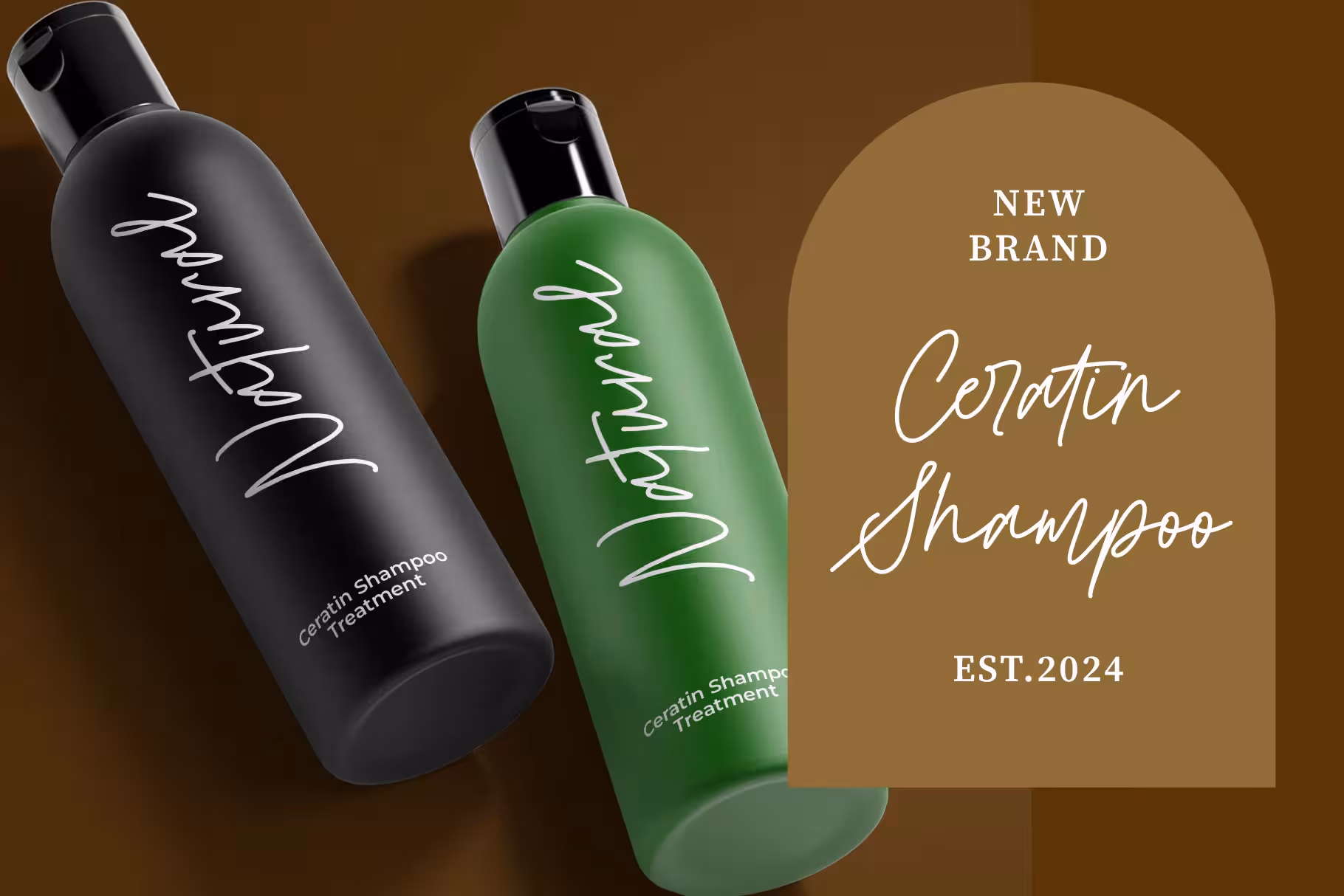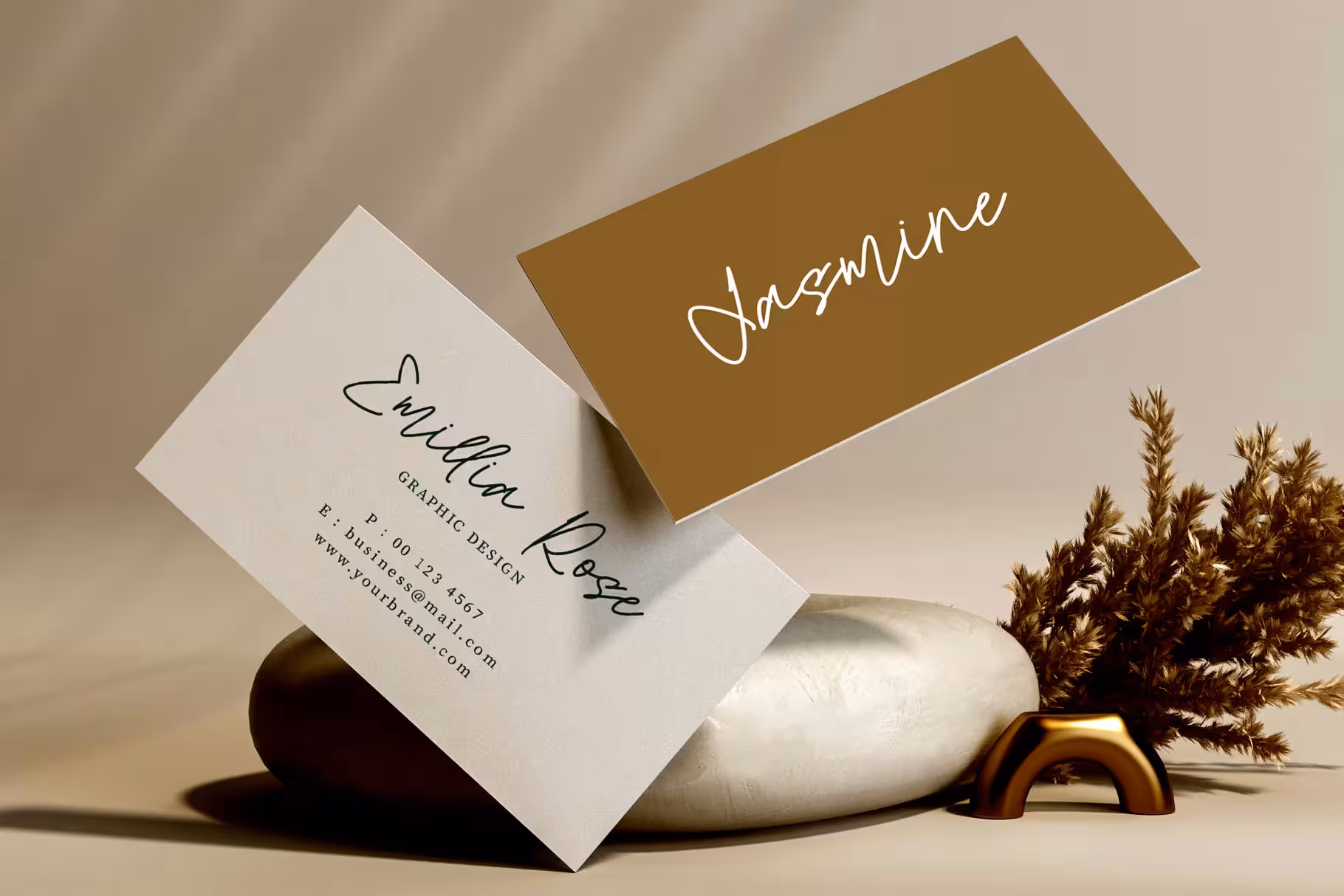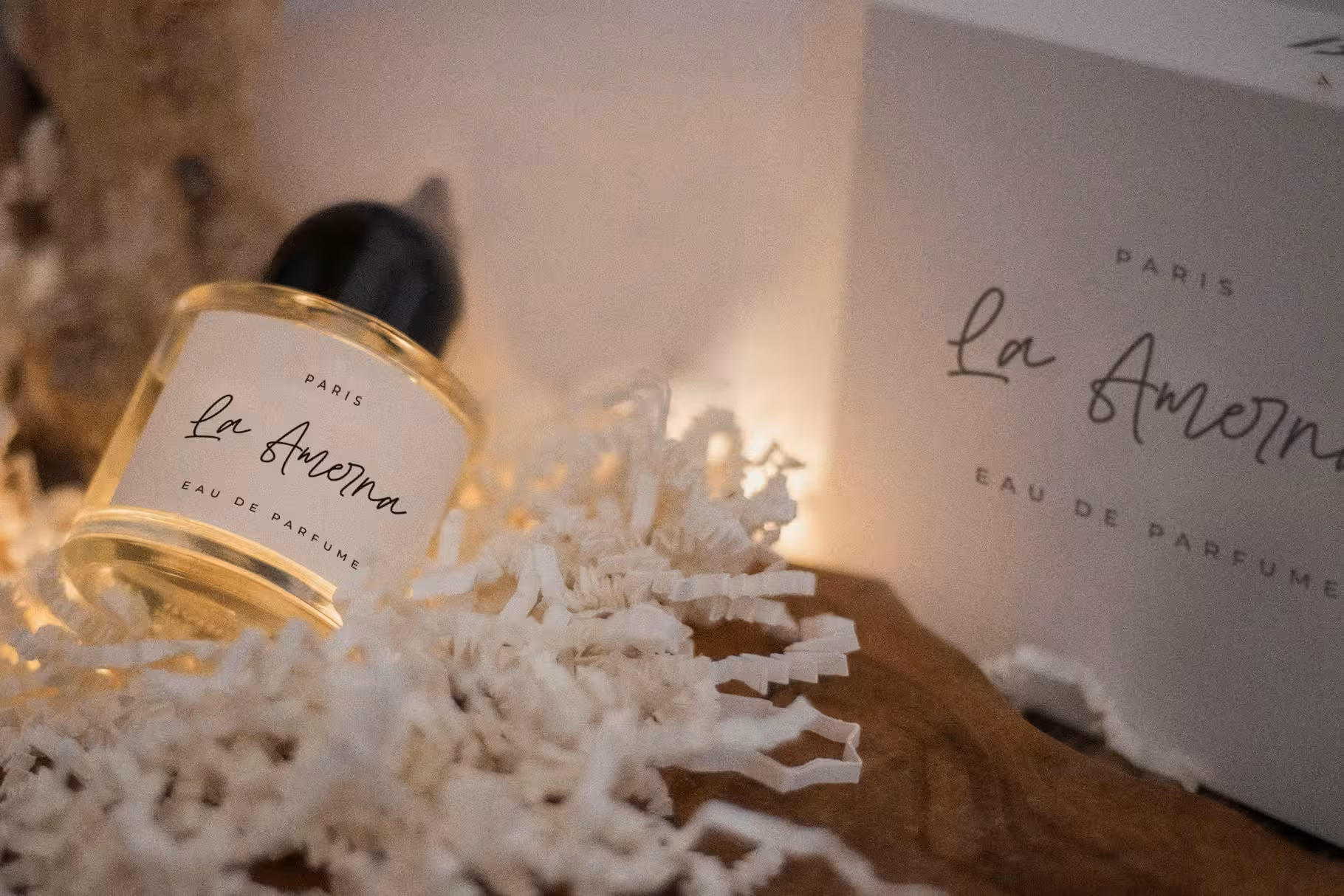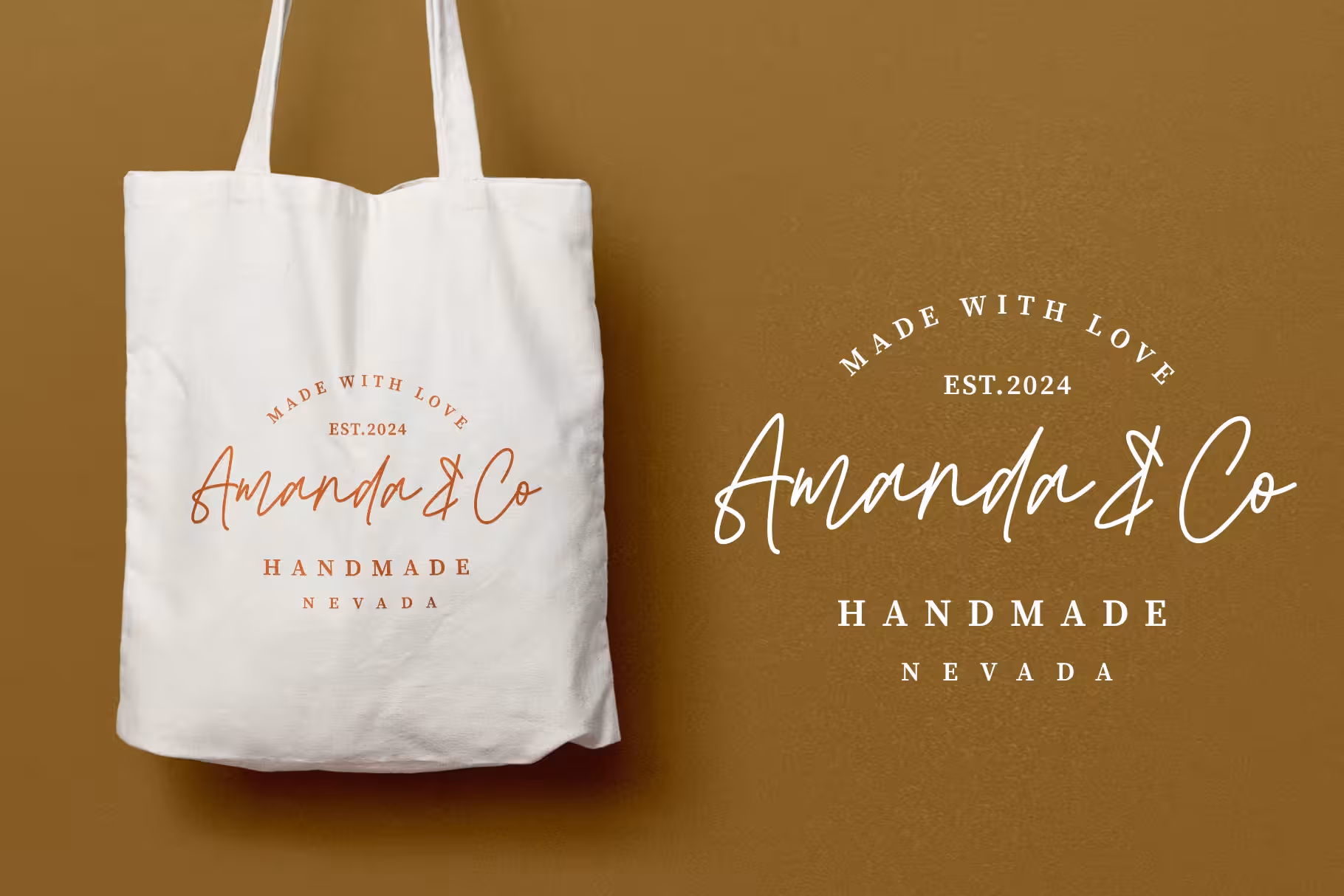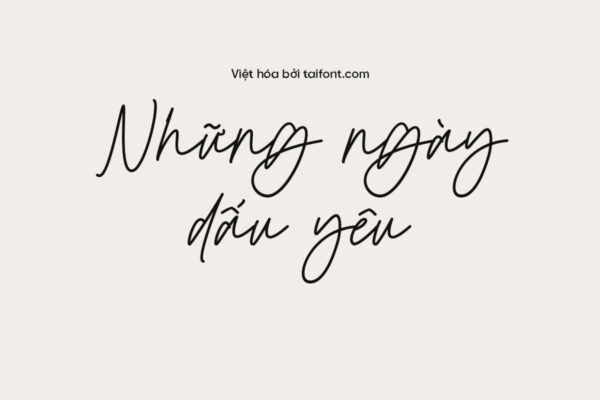
Giới thiệu về Font TF Herattey Việt hóa
TF Herattey Việt hóa là một font chữ viết tay (script font) nổi bật với vẻ đẹp thanh mảnh, tinh tế và đầy duyên dáng, mang đến phong thái nghệ thuật và cá tính. Font này gợi cảm giác như những nét chữ ký được viết tay một cách tự nhiên, uyển chuyển nhưng vẫn rất rõ ràng và dễ đọc, lý tưởng để tạo điểm nhấn riêng biệt và thu hút mọi ánh nhìn.
Với sự duyên dáng trong từng đường nét và tính thẩm mỹ cao, Herattey là lựa chọn hoàn hảo cho các thiết kế muốn truyền tải sự tinh tế, cá nhân hóa và một chút nghệ thuật, đặc biệt là trong các lĩnh vực:
- Thiết kế thời trang: Hoàn hảo cho các thương hiệu thời trang cao cấp, đặc biệt là thời trang nữ. Font này có thể được sử dụng cho logo, nhãn mác sản phẩm, lookbook, hoặc các chiến dịch quảng bá bộ sưu tập. Herattey giúp truyền tải vẻ đẹp thanh lịch, đẳng cấp và độc đáo của trang phục, nâng tầm giá trị thương hiệu.
- Túi xách da cho nữ: Lý tưởng để in dập, khắc laser hoặc thêu các logo, tên thương hiệu, hoặc họa tiết chữ lên túi xách da, ví da, hoặc các phụ kiện da cao cấp. Font này giúp tạo cảm giác về sự sang trọng, tinh tế và một chút phong cách thủ công, nâng tầm giá trị sản phẩm.
- Thiết kế thiệp: Phù hợp để viết lời chúc, lời mời, hoặc các thông điệp cá nhân trên thiệp sinh nhật, thiệp kỷ niệm, thiệp cưới. Nét chữ viết tay thanh lịch của font sẽ làm cho mỗi tấm thiệp trở nên độc đáo, ấm áp và đầy ý nghĩa.
- Name card: Tuyệt vời để sử dụng trên danh thiếp, đặc biệt cho các ngành nghề liên quan đến nghệ thuật, sáng tạo, hoặc các cá nhân muốn tạo ấn tượng độc đáo và cá tính. Font này giúp name card trở nên chuyên nghiệp, nhưng vẫn mang đậm dấu ấn riêng và dễ nhớ.
- Nước hoa: Hoàn hảo để sử dụng trên bao bì sản phẩm, nhãn chai, hoặc các chiến dịch quảng bá nước hoa. Font này giúp khẳng định chất lượng, sự sang trọng và vẻ đẹp tinh túy của sản phẩm, thu hút ánh nhìn của khách hàng và truyền tải thông điệp về sự quyến rũ, đẳng cấp một cách cá tính.
Với TF Herattey Việt hóa, bạn có thể dễ dàng thổi hồn nghệ thuật, sự tinh tế và cá tính vào các thiết kế, tạo ra những sản phẩm không chỉ đẹp mắt mà còn đầy cảm xúc và sức hút đặc biệt.
Font Việt hóa TF Herattey